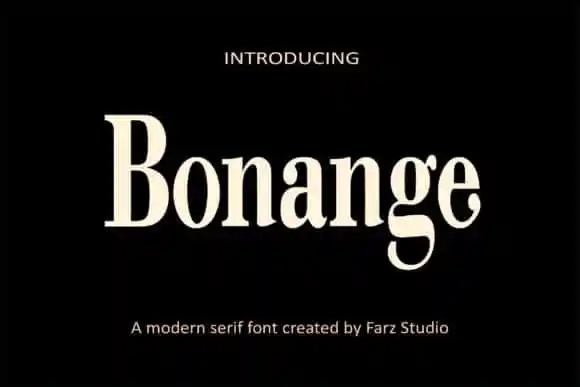
A Bonange Serif Font é uma tipografia serifada que surgiu da criatividade do Farz Studio, apresentando um estilo elegante, luxuoso e moderno. Desenvolvida para atender aos projetos de temas de luxo, esta fonte se destaca como ideal para aplicação em jornais, mídias sociais, marcações, logotipia e diversos outros ambientes que exigem uma dose extra de sofisticação e estilo único. Sua elegância é perfeita para adicionar um toque distinto a qualquer projeto visual. Esta fonte não só trará classe aos teus designs, mas também oferecerá inúmeras possibilidades criativas. Adentre em seus estilos versáteis e transforme simples ideias em verdadeiras obras de arte com esta Bonange Serif Font. Estamos ansiosos para vê-la ser usada no seu próximo projeto!